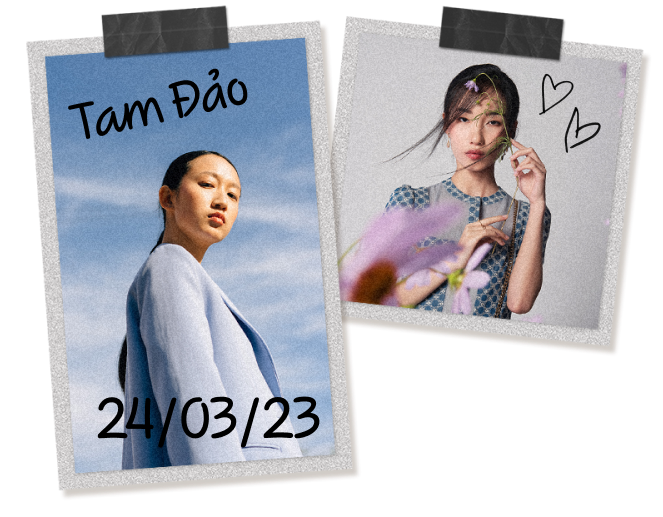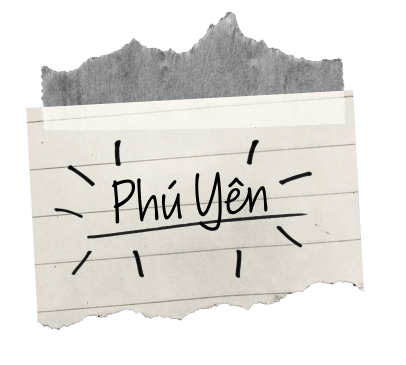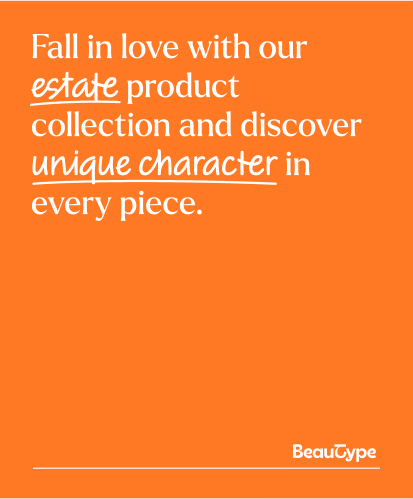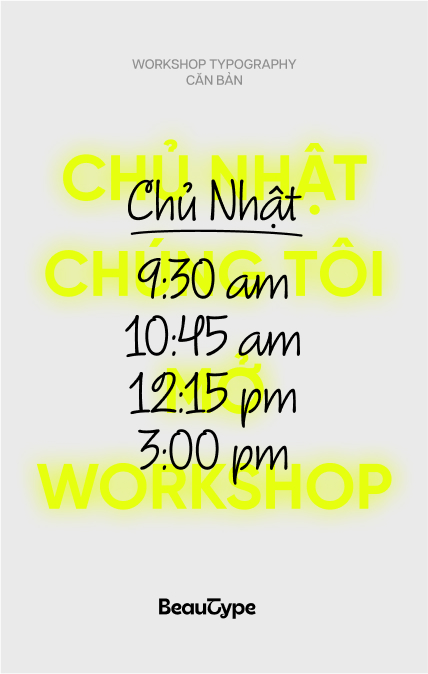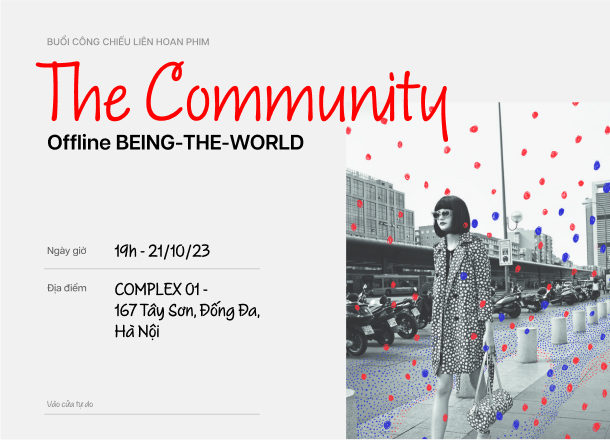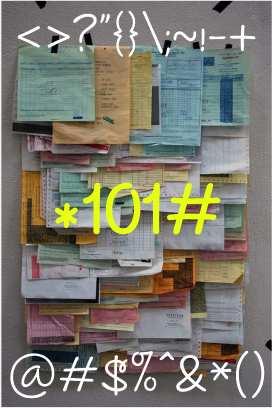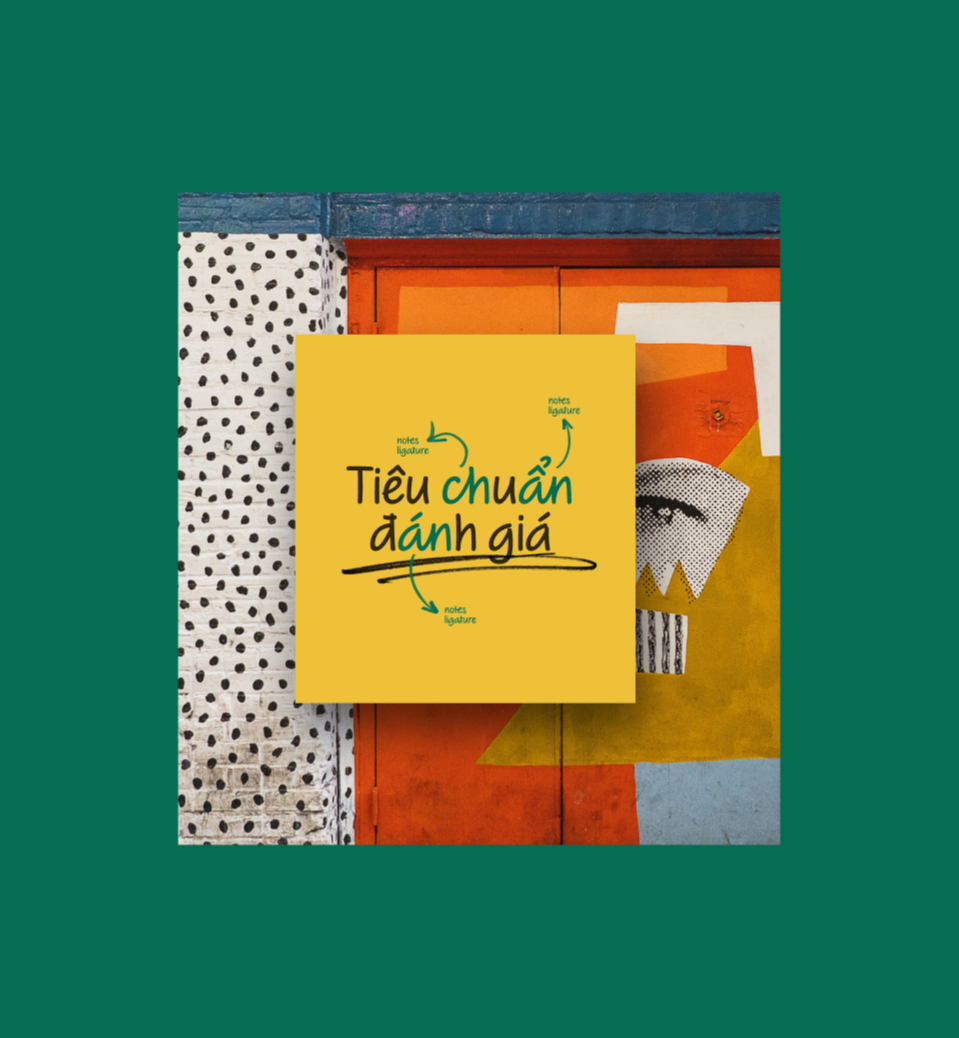
BT Brainstorm
BT Brainstorm là bộ script typeface với hai style Marker và Rollerball được phát triển bởi BeauType Studio nhằm mô tả lại chữ viết tay sử dụng 2 loại bút tương ứng là bút marker và bút bi.
Kết hợp linh hoạt
Với việc tái hiện nét chữ tự nhiên ở tốc độ viết vừa phải, dễ đọc, BT Brainstorm hoàn toàn có thể sử dụng độc lập hoặc kết hợp linh hoạt cùng với các bộ typeface khác để mang lại cảm giác con người, thân thiện cho thiết kế.
Hệ thống ligature
Điểm khác biệt của BT Brainstorm nằm ở bộ ligature (chữ ghép nối) phong phú, giúp mô phỏng sát nhất những nét bút viết tay tự nhiên của con người mà không làm mất đi tính hệ thống của font chữ
- Marker
- Rollerball Pen
Hỗ trợ đa ngôn ngữ
BT Brainstorm hỗ trợ đa ngôn ngữ các bộ chữ gốc Latin, một trong số đó là tiếng Việt. Việc xây dựng một bộ font đa ngôn ngữ giúp cho tiềm năng ứng dụng và sáng tạo đối với bộ font là vô tận.